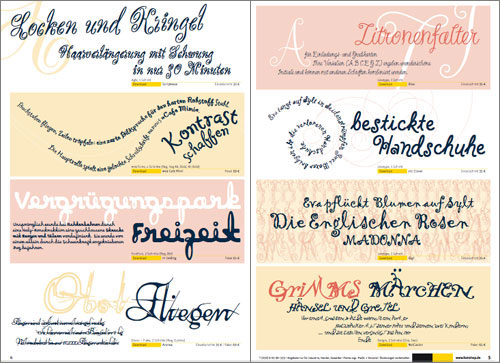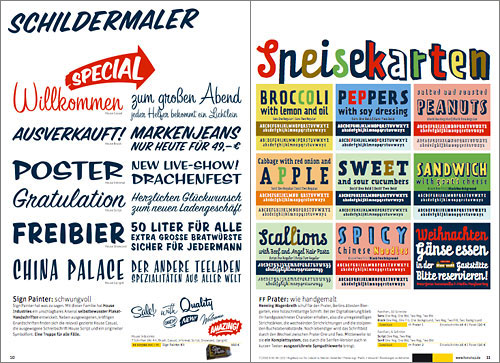
»fonts Extra Script« erschienenAuf diese Broschüre sind wir aus zwei Gründen Stolz: a) sie war
nicht geplant und b) sie ist sehr ansprechend geworden: fonts Extra
»Script«. Zum ersten Mal widmet FontShop einer einzelnen Schriftart
ein Sonderheft. Auf sieben Doppelseiten tauchen wir in die Script-Welten
»Locken«, »Bestseller«, »Meisterfedern«,
»Schildermacher«, »New Kids« und »berühmte
Handschriften« ein. Das kostenlose Heftchen sollte spätestens am
Anfang Dezember traf die FontShop-Marketing-Abteilung den Entschluss, sich
selbst ein Weihnachtsgeschenk zu machen: eine schöne Extra-Drucksache, die
sich den emotionalsten Schriften widmen sollte, den Schreibschriften. Wir
tauften das Heftchen fonts Extra Script und entwickelten mit den moniteurs binnen
weniger Tage Konzept, Inhalt und Gestaltung. Am Ende waren wir selbst
überrascht von den starken Auftritten, die unsere Lieblings-Scripts
entfalteten.
![]() Titelseite der fonts-Extra-Script-Broschüre; aufmerksame Fontblog-Leser (microboy) hatten sie bereits im Bericht über unsere kleine interne Ausstellung auf einem Foto entdeckt ![]() Doppelseite mit Locken- und Kringelschriften aus fonts Extra Script ![]() Doppelseite mit eindrucksvollen Plakatschriften aus fonts Extra Script Eigentlich sind wir auch noch auf etwas anderes Stolz: dass solche Broschüren gewünscht werden (siehe microboy-Kommentar) und FontShop in der Lage ist, weiterhin Drucksachen für Schriften zu produzieren. Die werden nämlich immer seltener, weil Schrift-Entwerfer und Schriftenhäuser zunehmend ihr Heil im Internet suchen (und dort ihre Marketing-Euros versenken). Nichts gegen das www (hier schreibt schließlich ein Blogger), doch die Vielfalt der Schriften verdanken wir der Gutenberg-Technik und nicht dem Internet. Trotzdem: hier gibt’s fonts Extra Script als PDF zum sofortigen Download (3 MB) ... das hat ja auch seinen Charme, oder? ;-) Herausgegeben: Fr - Januar 13, 2006 at 09:51 vorm. | |